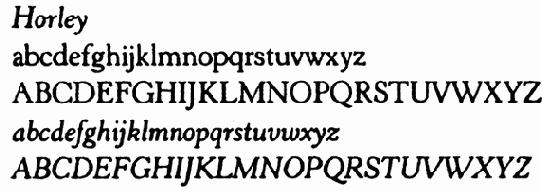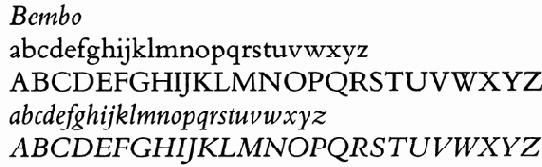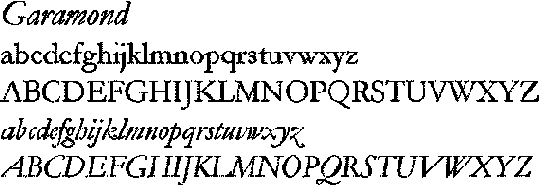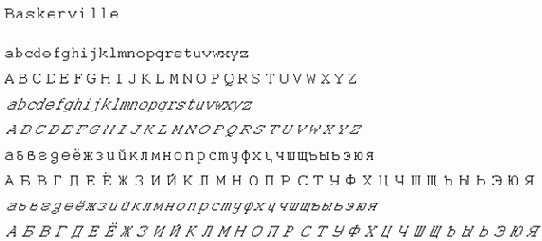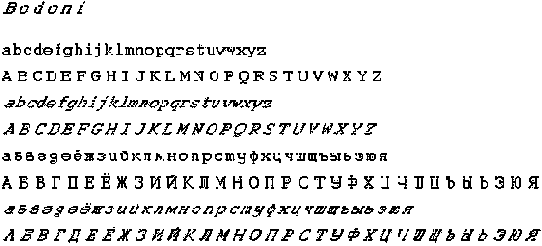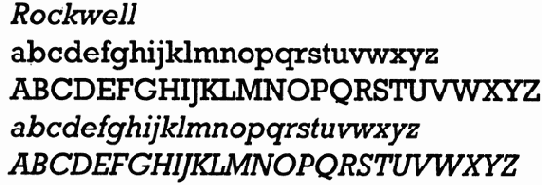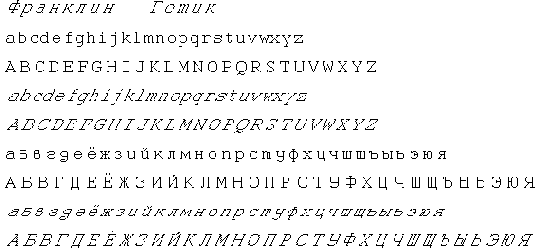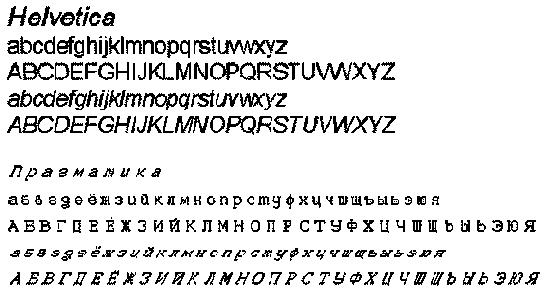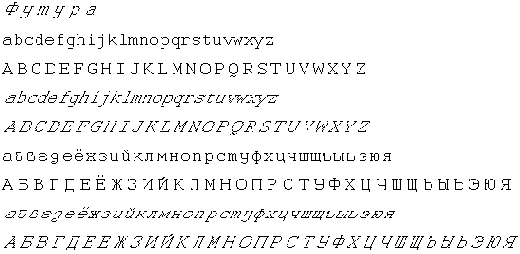
Классификация шрифтов
Согласно принятым соглашениям, большинство шрифтов объединяются в группы, часто в соответствии с историей их создания. Российский стандарт ГОСТ 3489.1-71 "Шрифты типографские" определяет шесть основных групп шрифтов.
Британский стандарт BS 2961:1967 определяет восемь групп шрифтов. Но довольно часто используется и "традиционная" номенклатура, применяемая до появления стандарта.
Ниже приведены шрифты согласно классификации по стандарту BS, а также соответствующие традиционные названия в скобках.
Готические шрифты использовались при производстве первых книг (в 1450-е годы, в Германии). Первые романские шрифты ("roman") были получены через 20 лет в Италии. Печатник из Венеции Николаус Йенсен скопировал их с итальянских рукописей XV века.
Антиквенные венецианские шрифты (Humanist (Venetian)). Антиквенными называется группа шрифтов, имеющих засечки. Характерным представителем и "родоначальником" этой группы были шрифты Humanist, похожие на элегантные рукописные и имеющие наклонный нажим, придающий им каллиграфическое начертание. Их отличительный признак – наклонная черта буквы "e", воспроизводящая соответствующую букву из рукописей того времени.
В качестве примеров можно привести шрифты Centaur, Cloister Old Style, Horley Old Style, Kennerley, Veronese, которые все основаны на печатных образцах 1470 и 1480 гг.
Шрифты старого стиля (Garalde (Old Face)). Увлечение шрифтами Humanist оказалось весьма непродолжительным. Через 25 лет после Йенсена печатник Альд Мануций, снова в Венеции, предложил новую серию шрифтов, позволяющих достичь существенной экономии при наборе без ущерба для четкости, а литеры были более правильными и твердыми. Новая разработка доминировала в типографском деле в течение следующих двух веков.
Шрифты Garalde менее каллиграфические по своему виду, чем шрифты Humanist, и в них возвращена горизонтальность перекладины в букве "e". Они также имеют наклонную ось овала и достаточно экономичны.
Они имеют небольшое очко строчных знаков, но очень элегантный дизайн. Это классические книжные шрифты.
Шрифты Garalde встречаются во многих вариантах, отражающих различные национальные и культурные особенности, приобретенные после первоначального своего появления. Современные разработки, конечно, были созданы машинным способом; многие из них были созданы в начале тридцатых годов XX столетия.
Они включают в себя шрифты Bembo (1490, Италия); Garamond (1530, Франция); Ehrhardt (1680, Германия); Caslon (1720, Англия).
Ряд шрифтов классического стиля, в которые были привнесены некоторые новые элементы при сохранении основных старых характеристик, был создан в середине XIX века. К ним относятся Old Style (1852, Шотландия); Imprint (1912, Англия).
Шрифты переходного стиля (Transitional). В середине XVIII столетия влияние гравирования в технике письма и типографском деле стало более ощутимым. Гравированные медные литеры придавали регулярный и механический облик тексту; эта тенденция способствовала многим нововведениям в металлическом наборе того времени. Это была "эпоха рационализма", когда предпочтение отдавалось однородности и симметрии. В то же время, ряд достижений в технике печати и появление более гладкой бумаги привели к появлению более тонких штрихов и более изысканному контрасту основных и соединительных элементов литер.
Шрифты переходного стиля отличают более вертикальная ось овала, для них допускается больший контраст. Серифы по-прежнему используются скругленные.
Наиболее популярными на сегодняшний день шрифтами переходного стиля являются Baskerville (1760, Англия); Fournier (1760, Франция); Bell (1780, Англия); Scotch Roman (1790, Шотландия).
Шрифты нового стиля (Didone (Modern)). Тенденция к однородности, механическому характеру и симметрии, господствующая в ходе всего XVIII века, достигла своей кульминации в начале XIX века и способствовала появлению высокооднородных, высокоструктурированных шрифтов.
Шрифты нового стиля имеют полностью вертикальную ось овалов, горизонтальные серифы и резкий контраст между основными и соединительными штрихами.
В качестве наиболее известных примеров можно привести шрифты Bodoni (1810, Италия); Walbaum (1820, Германия); Modern Extended (1830, Шотландия).
Брусковые шрифты (Slab-serif (Egyptian)). Промышленная революция и оживление коммерческой деятельности, которой она сопровождалась, способствовали появлению новой моды в типографском деле, которая была свойственна викторианской эпохе – кричащие и тяжелые шрифты.
Первые, ранние версии шрифтов представляли собой шрифты Didone (Modern) со смелым начертанием (1810-е годы). Для этих шрифтов характерны линейные засечки как со скобками, так и без. Некоторые из этих шрифтов были использованы в качестве наборных, особенно Clarendon, первый шрифт, разработанный и используемый в качестве жирного (1845).
Все остальные шрифты согласно данной схеме классификации представляются как гибриды основных шрифтов. Многие из них содержат новые дизайнерские решения, вызванные применением цифровых технологий, сканирования и возможностей электронной обработки и улучшения вида символов.
Теперь выберем шрифт и используем его для разработки дизайна книги.